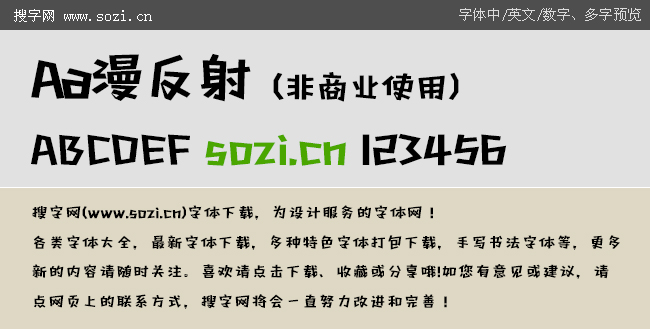
Aa漫反射
搜字網(wǎng)給大家提供一款A(yù)a漫反射(非商業(yè)使用)中文字體下載,Aa漫反射是一款卡通藝術(shù)字體,字體筆畫略帶傾斜,字形變化隨意,充滿童真,具有濃厚的卡通風(fēng)格。適合應(yīng)用于藝術(shù)設(shè)計(jì)、平面宣傳設(shè)計(jì)、網(wǎng)頁設(shè)計(jì)、海報(bào)設(shè)計(jì)等應(yīng)用(此字體為個(gè)人非商用版,商用可以聯(lián)系QQ:1006760504)。